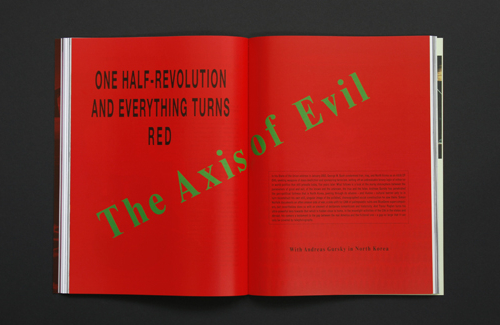
上个月最引人注目的设计事件,莫过于全球最大的家居连锁宜家家居(IKEA)更换了自己的字体,从原先的 IKEA Sans(基于Futura)改成 Verdana。瑞典民间的说法是,宜家的目录册印刷量仅次于《圣经》。如此大的影响力,使得使用新字体的2010年目录册一经出版,就引起了大批设计和字体爱好者的注意。 Facebook 和 Twitter 上很快出现了大面积的震惊和批评的声音,设计师社群也出现了长篇的激辩。 网上发起请愿签名反对这一决定,至今人数已经接近7000。网上的巨大反应也引起了主流媒体的注意,包括美联社、《纽约时报》和《时代》杂志等都对事件进行了报道。
毋庸置疑,宜家这一更换字体的做法必定是经过理性思考和经济衡量过的。宜家的解释是,这一更换完全是因为 Verdana「更加经济和高效」,可以跨国家跨平台使用。实事求是的说,单就字体功能性来讲,Verdana 的确占上风。Verdana 的大写「I」和小写「L」显然比 Futura 识别度高,在屏幕显示也胜一筹,也有意见称 Verdana 的数字设计要好过 Futura。进一步说,Verdana 的采用成本必然要比 Futura 要低(现在主流的平台都搭载 Verdana,而 Futura 的授权要花上成百甚至上千美元),而且其跨平台(比如从平面到 Web)的一致性也优于前数字时代的 Futura。
尽管从以往经验看,经典设计的新变化总是会带来反对声音。但对宜家这次换字体不依不饶,也并非是纯粹的惯性心理作祟:Verdana 诞生于 Web 1.0时代,专门为屏幕小尺寸显示而设计,是 Windows 很多版本的默认字体,与 Arial 和 Comic Sans 等一样,被全世界的办公系统滥用,形象和气质都与一向挥着设计大旗的宜家的企业形象难以拉上关系。 因此官方「高效和经济」这一解释显然不能满足很多崇尚设计的消费者。 在批评者眼里,已成为某种宜家从「瑞典风格的现代主义」堕落到「同质化和全球化」的象征。
Futura 是1920年代现代主义的经典字体,由 Paul Renner 设计,灵感来源于俄国的构成主义,有着深厚的历史渊源和文化继承。宜家使用 Futura 长达五十多年,Futura 已经植根于宜家的设计传统,成为宜家企业形象不可分割的一部分,与宜家注重设计的哲学相得益彰。而现在宜家忽然为了一个「成本」和「通用」的理由,悄然改变了自己具有重要识别度的形象元素,将自己几十年来建立的视觉形象置于一个令人困惑的危险境地,同时也伤害了以设计为上的心理定位,怎么看也是一个得不偿失的做法。《卫报》写到:「(Verdana)给人感觉与一个根基于设计的瑞典公司并不相称,看上去反而更像一个不会在让人想看第二次的公司」。而美国字体设计协会(TDC)前主席 Allan Haley 的评论也讲出了很多人的心声:「这一做法极有风险……(此次变化后,宜家)将和任何使用 Verdana 的公司变得一样。它的新闻册与街边饭馆的菜单已经无异,(因为Verdana)无法达到品牌区分的目的。」
然而宜家这一令人不解的设计决策,却看似与当今潮流吻合。我们不妨回顾一下近年来与经典审美格格不入的设计潮,看能否帮助我们了解宜家的做法。 让世界哗然的2012伦敦奥运会徽发布不久, 著名的设计师和评论家 Michael Bierut 撰文描述设计界这一被称之为「新丑陋(New Ugly)」的潮流。被评论的代表性设计包括:Wolff Olins 另为纽约市(NYC)设计的标志,被形容似「交通高峰期挤在市中心的四号车里」;电子绘图板 Wacom 的新商标(「妈妈你什么时候学了Photoshop」);炙手可热的德国文化杂志《032c》(打破了平面设计最后的「禁忌」——横竖拉伸字体)等等,都是视觉上十分荒唐而不「专业」的设计。这样的例子在今天也没有停止,百事的「微笑」新商标和奥迪汽车(Audi)的商标换字就是这一视觉困惑潮流的延续。
探其究竟,大部分「新丑陋」潮流的设计背后,设计师都有一套自己的解释。Wolff Olins 对于伦敦奥运会徽的解释是:「想要挑起公众的注意力和反应」,「律动」和「活力」也是关键词。而纽约市标志的字体,则表达了「纽约人的粗放」,同时也在操作上做为一个不同图像和色彩表达的媒介。英国《Creative Review》的评论直截了当的点名了 Wolff Olins 的意图:「当我们身边的商标设计都依据一个巧妙逢源的主流美学标准,那么唯一可以出众的方法就是有意拒绝这些标准。」
而《032c》的设计师 Mike Meiré 也有相似的观点:「现在有太多杂志都在装酷、装老练、装有内涵。它们看起来全都一样。对于这一点,我已经有些厌倦了。」这位有专业素养,曾经出品过很多在业界声誉极高的杂志设计的设计师,也刻意反主流,丢下了所有的科班规条。当有著名杂志设计评论指出《032c》的设计除了「丑陋」之外无法形容时,出版人和设计师都满意地笑了:「生活总有不同的美可以呈现。如果人们觉得(这些设计)使人困惑,那是因为我们太习惯传统设计的高效、流水线和正确性了。」
另一方面,尽管比起时尚和建筑,平面设计鲜能引起公众注意,而事实上,众多标榜「挑动」的争议性平面设计的出现显然真的挑起了公众的神经,达到了设计师的目的。伦敦2012年奥运会的会徽的发布,就引起了大众的关注,即便媒体上最常见的公众评论是「令人作呕」,和「我5岁的孩子也能画出来」。而宜家换字体的事件,也有意无意地让主流媒体上难得地发表了主张「应该关注字体」的文章。
在这些令人不解的设计背后,「反传统」、「挑动反应」、「反主流」都成为它们反其道的关键词。而 Mike Meiré 们所说的,对主流设计的「审美疲劳」,也会引起很多人的共鸣。 这些到底是对设计同质化时代的激烈反应,还是要促成一个真实的文化变革,评论界对各个作品有不同看法。事实上,这一波「丑陋」的潮流最早可以追溯到1990年代初的「反主流」潮。当时《Eye》杂志就发表了极有分量的一篇评论《丑陋狂热》(Cult of the Ugly),评论当时出现的一些实验设计。
当时的评论与现在的意见类似。尽管视觉上不符合传统审美,但只要是设计师们有意图的,根据「形式随机能」(Form Follows Function)进行的设计实验和新风格的探索,评论界和设计师都比较认可。设计师们这种对于同质化设计和经典设计的反叛性回应,对另一种文化和精神的表达,是值得赞赏的。但为了丑陋而丑陋,抑或是缺乏智慧、训练和品味,不得已而成的「丑陋」,则是对设计的亵渎。 然而正如 Michael Bierut 指出,尽管艺术的许多变革都是由一次次不入传统眼的风格变化开始的,但「毕加索和史特拉芬斯基的出现毕竟只是少数」。这「丑陋」潮中究竟哪些是业余人士的信手涂鸦,哪些是稍纵即逝的潮流,哪些是值得注意的变革,需要单独评判,细细咀嚼。
谈回宜家换字体。看似与反主流的新「丑陋」潮流一样,都引起了公众反应和专业人士的不满,但评判它是否是一个设计层面的堕落,要看这个做法背后的意图。这是否是一个从设计高度深思熟虑过的做法?从官方的说法看,引人怀疑。倘若真是管理层为了节约开支而没有做设计上的考虑,那么这是宜家、也是商业平面设计的一大悲哀;而如果全球化和同质化是宜家设计要表达的新理念,那么大可赞赏一下宜家的设计探索精神和商业勇气。
昨天正好去了宜家,依旧Futura。。。至少上海的IKEA还没改过来
宣传册改了一阵了,上海的
1. The IKEA futura was different to normal ones, it was modified by Stockholm Design Lab and called “IKEA Sans”
2. 032c isnt quite the same, It is making an anti-statement and social commentary, and IKEA is quite different if not opposite.
3. When desktop publishing makes design management more and more efficient, it is no argument to say we change for the future because “更加经济和高效”。
4. to the recent so-called “ugly” design, maybe Walter Benjamin was on something,
“During long periods of history, the mode of human sense perception changes with humanity’s entire mode of existence. The manner in which human sense perception is organized, the medium in which it is accomplished, is determined not only by nature but by historical circumstances as well. “–The Work of Art in the Age of Mechanical Reproduction
But I dont think IKEA is on the way to evolution by retreating to the mundane. It is a lazy managerial decision to “change” for the better future. since the advent of WOFF and other font sharing server applications, such “理性思考” decision is not quite foresighted.
alright.
1. ye i know.
2. i agree. i think i did imply this point in the article, both unconventional design, but 032c made a cultural sense.
3/4. agree, which is also the point i wish to make in the article.
Frieze has an article with short mention of IKEA.
访问032C的出版人的时候正在想怎么开始这个New Ugly的话题,结果他自己主动开始说了,说他以为改变会使设计师赞同普通读者反对,没想到结果相反。
怎么样的设计最后都逃不过对设计动机道德上的评价,怎么样的设计师最后都逃不过对自己节操的考量。设计如果会有什么真正变革的话,从来只可能是社会主流的价值发生变化。